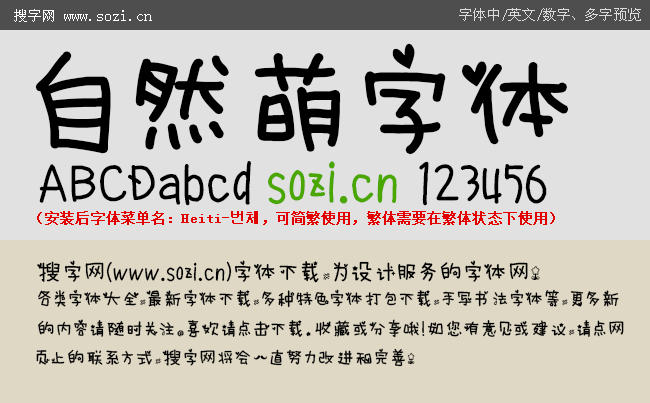
自然萌字體
搜字網(wǎng)給大家提供一款卡通手寫風(fēng)格的手機(jī)中文字體下載。名字叫自然萌字體,這款手機(jī)字體是仿照兒童手寫風(fēng)格的卡通手寫字體,結(jié)構(gòu)帶有POP字體風(fēng)格,字體間還插入了大量有趣卡通圖案,特別適合喜歡手機(jī)字體個(gè)性一些的朋友在手機(jī)上安裝使用。